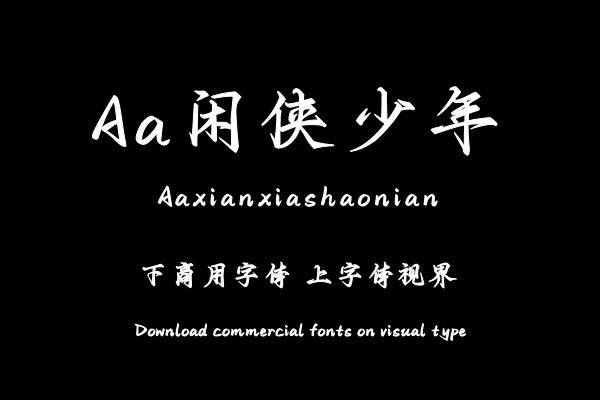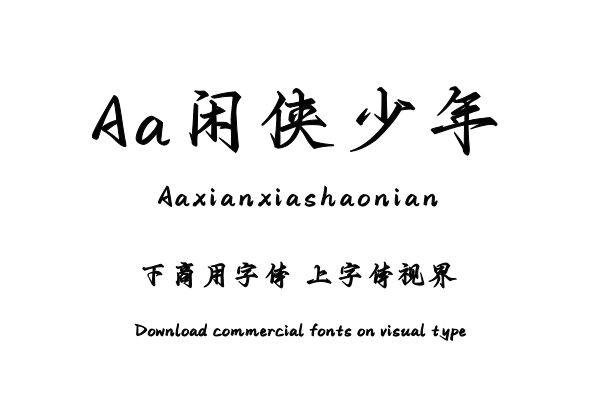
该字体字形端正美观,很好的把瘦金体的骨架和传统书法结合在一起,再加上干劲有力的笔触,棱角分明,让整个字体更加醒目亮眼。连笔自然优美,保留了连笔之间的细丝,使整个......购买须知:“下载服务费”与“字体VIP”所获得字体 仅用于个人非商用, 商用请联系付费授权。本字体为电脑用字,手机没有root权限不支持直接手机换字(手机如何root,请自行百度搜索教程)。购买前请先 了解清楚后再付款 ,字体为虚拟产品无法回收 一旦购买不支持退款。